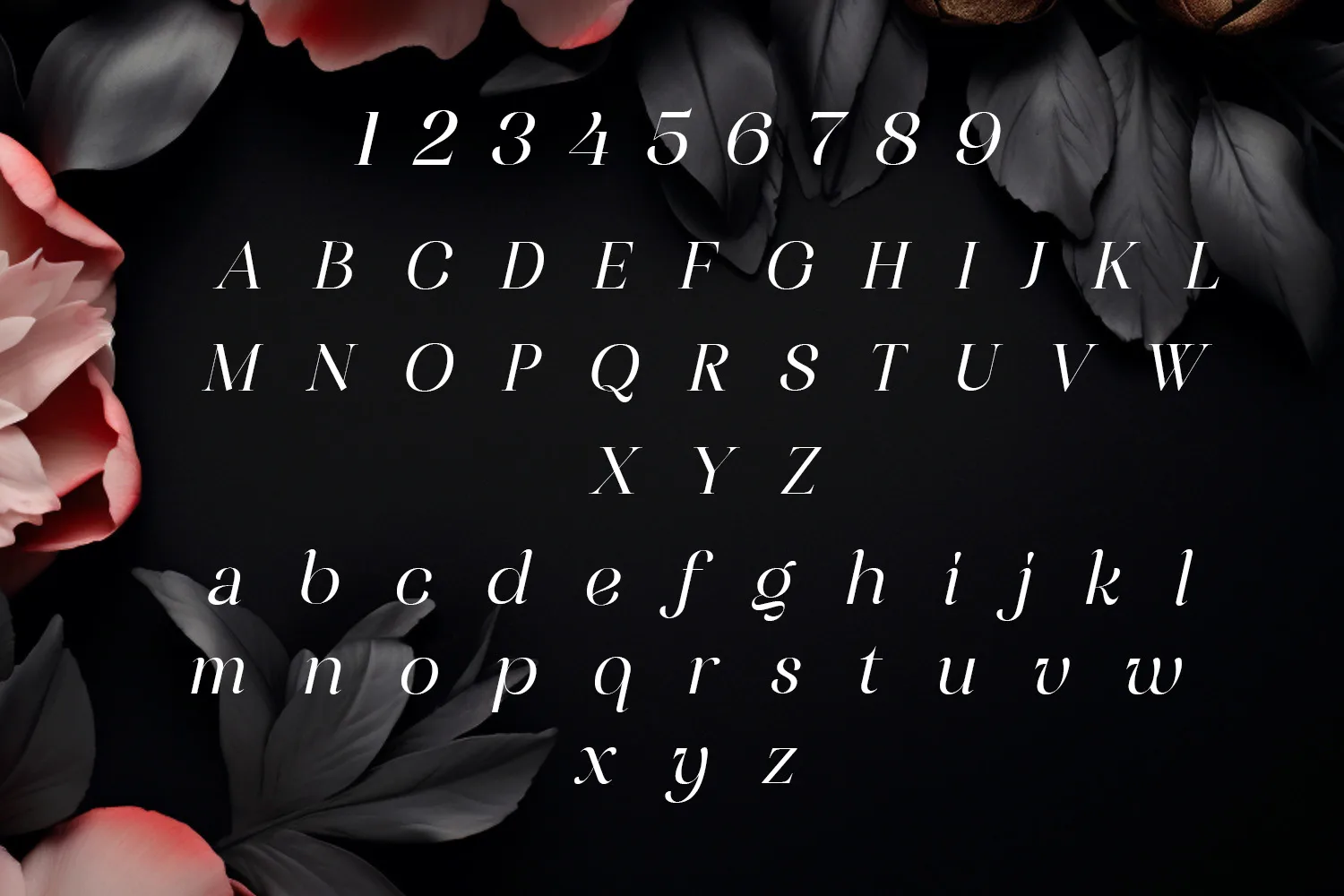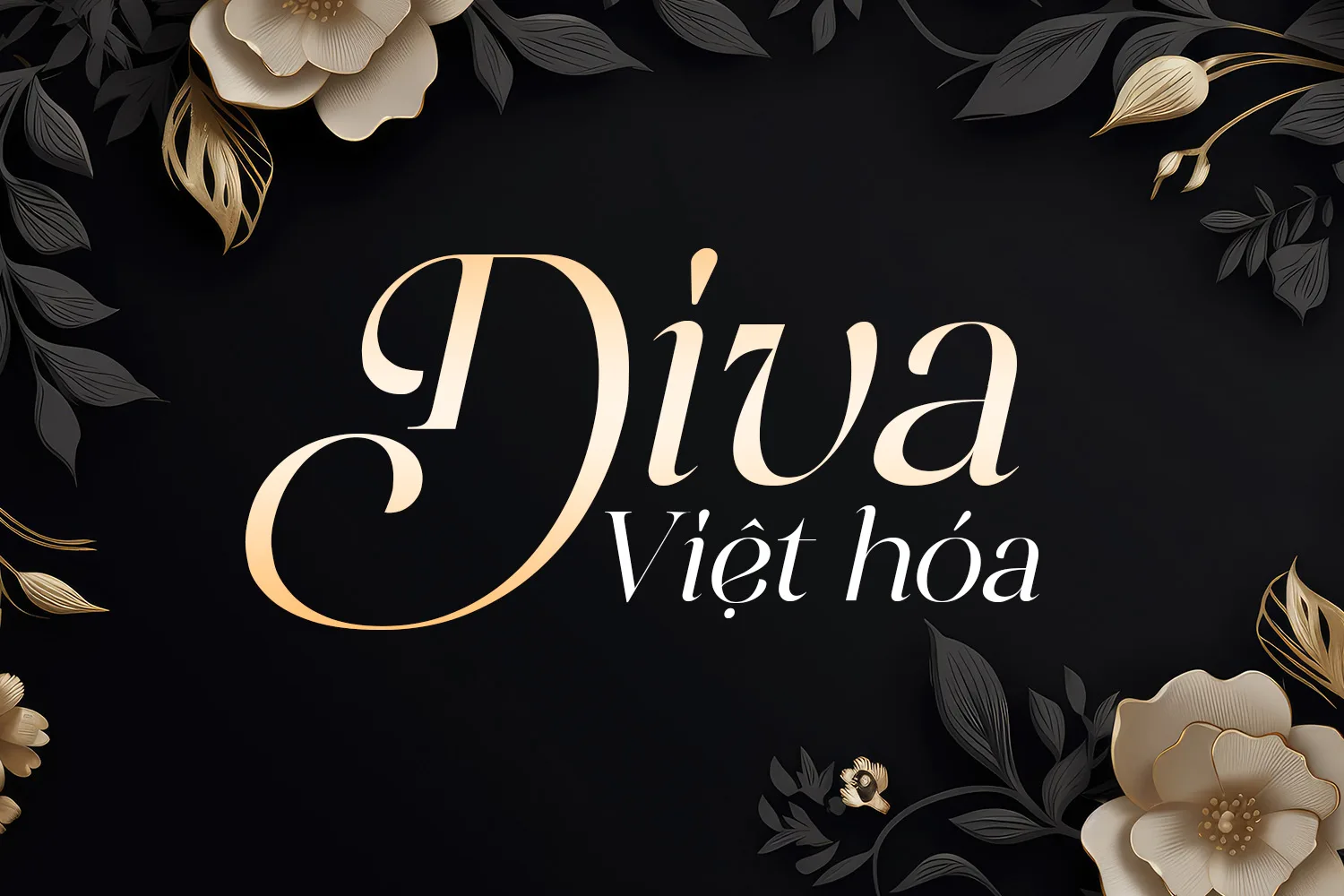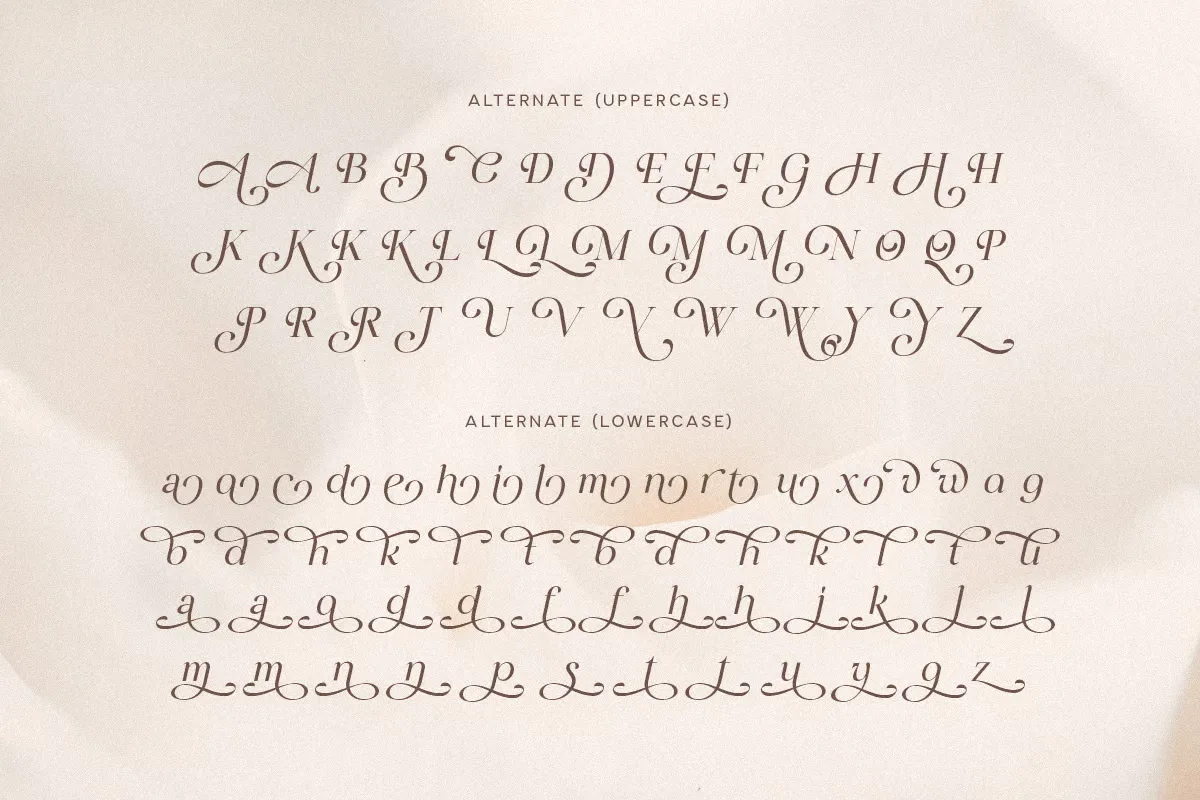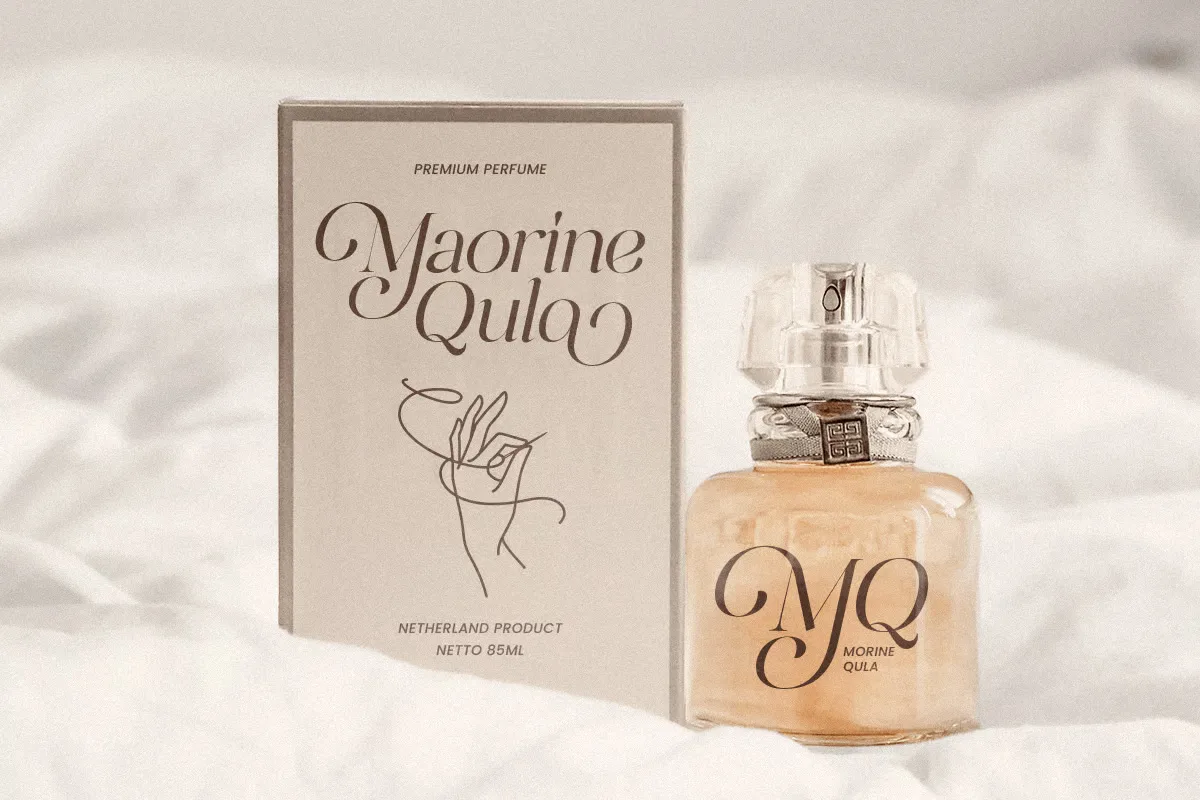
DVN Diva Việt Hóa – Font chữ uốn lượn thanh thoát và quyến rũ đúng chất ‘Diva’
DVN Diva Việt Hóa là một kiểu chữ italic serif cao cấp mang đậm phong cách thời trang và nghệ thuật. Những đường cong uyển chuyển kết hợp với các nét chân thanh đậm tinh tế khiến font trở thành lựa chọn lý tưởng cho các thiết kế mang đậm dấu ấn sang trọng, mềm mại và quyến rũ.
Font phù hợp cho các dự án như logo thương hiệu cao cấp, bìa tạp chí, thiệp cưới, mỹ phẩm, poster thời trang, hoặc bất cứ thiết kế nào cần sự nổi bật và thanh lịch.
Phiên bản Việt hóa được trau chuốt đầy đủ dấu tiếng Việt, giữ nguyên vẻ đẹp nguyên bản và hỗ trợ thiết kế dễ dàng hơn cho người dùng trong nước.